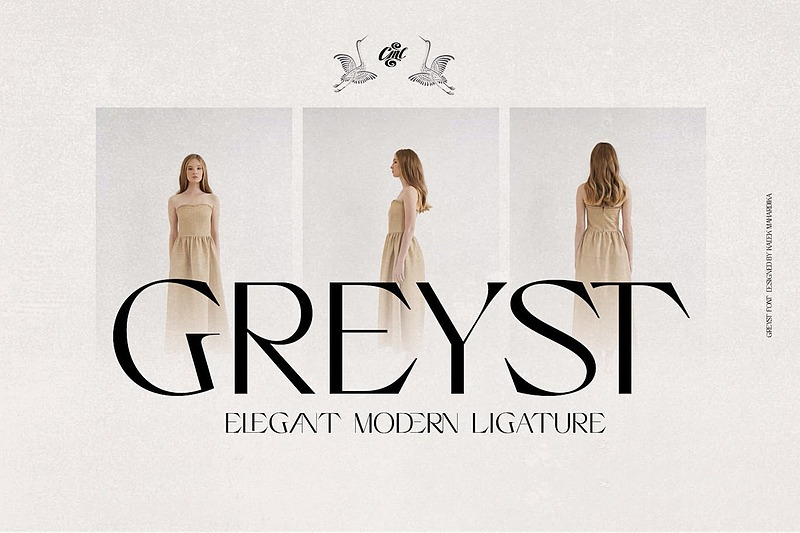
فونت انگلیسی گریست (Greyst)
فونت لیگاتور مدرن الگانت
گرِیست، فونت نمایشی ساده و منحصربه‌فرد با ده‌ها لیگچر. این فونت همه‌کاره برای برندسازی، پروژه طراحی وب، لوگو و موارد دیگر با پشتیبانی چندزبانه، اعداد و نمادهای کارنسی بهترین است.
• طبقه‌بندی: سریف
• فاصله‌گذاری: نرمال
• اندازه بهینه: هر اندازه‌ای